I den digitale tidsalder er skrifttyper mere end bare tekst; de er en fundamental del af brandidentitet, design og brugeroplevelse. To af de mest indflydelsesrige virksomheder inden for teknologi og design, Adobe og Apple, har begge en rig og kompleks historie med skrifttyper. Deres valg af skrifttyper har ikke kun defineret deres egne brands, men har også haft en dybtgående indflydelse på designverdenen som helhed. Lad os udforske deres rejse gennem typografiens landskab og se på forbindelsen til den klassiske skrifttype Garamond.
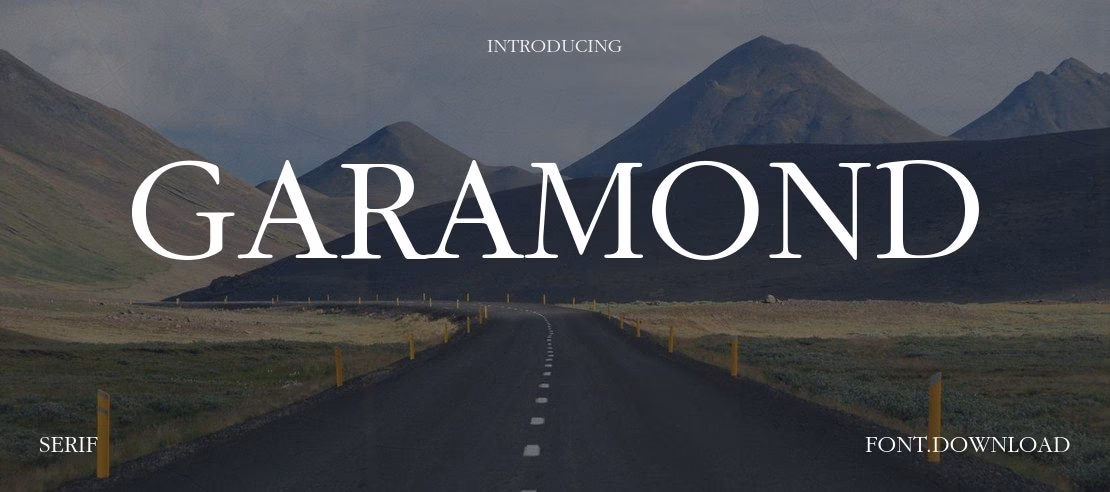
Adobe Systems, grundlagt i 1982 af John Warnock og Chuck Geschke, voksede hurtigt og blev en milliardvirksomhed. Deres succes bygger i høj grad på innovation inden for grafik og teksthåndtering, herunder den revolutionerende PostScript-standard og software som Adobe Illustrator og Photoshop, der blev standardværktøjer for grafiske designere. Introduktionen af Adobe Type Manager (ATM) i 1990 forbedrede visningen af skrifttyper på skærmen markant. Adobe har altid taget typografi meget alvorligt, en dedikation der var tydelig fra begyndelsen.
Under ledelse af Sumner Stone, Adobes typografidirektør fra 1984 til 1991, påbegyndte virksomheden et ambitiøst designprogram. De første skrifttyper i det vigtige Type 1-format blev hentet fra etablerede biblioteker som Linotype og ITC. Endnu vigtigere var initiativet til at genoplive og digitalisere klassiske skrifttyper. Dygtige designere som Robert Slimbach og Carol Twombly, hvis navne er synonyme med fremragende skrifttypedesign, arbejdede på at genskabe historiske perler, herunder Garamond og Caslon. Adobe skabte således sine egne, respekterede versioner af disse klassikere, hvilket cementerede deres position som en central aktør inden for digital typografi. Ud over genoplivninger skabte Adobe også nye, originale skrifttyper som Minion.
Adobe fortsatte med at innovere inden for skrifttypeformater og var medansvarlig for PostScript Type 3 og det spændende Multiple Master-format, der tillod ubegrænset interpolation mellem designvarianter – en sand teknologisk bedrift, selvom udviklingen desværre stoppede i 1999. Fra 1997 arbejdede Adobe sammen med Microsoft om OpenType-formatet. OpenType revolutionerede digital typografi ved at muliggøre smarte erstatninger for tegn (som ligaturer og små kapitæler) og forbedre understøttelsen af mange sprog, hvilket gjorde komplekse typografiske regler tilgængelige digitalt. Adobes OpenType-skrifttyper blev tilgængelige online i 2007.
Apple Inc. har ligeledes en fascinerende historie med skrifttyper, især i relation til deres branding. I over 18 år var Apples primære virksomhedsskrifttype en specialdesignet variant af ITC Garamond kaldet Apple Garamond. Denne skrifttype var tæt forbundet med Apple-brandet og blev brugt overalt – fra logoer og produktnavne på computere til reklamer, trykt materiale og virksomhedens hjemmeside.
Før Apple Garamond eksperimenterede Apple med forskellige visuelle identiteter. Deres tidlige logo med Isaac Newton var håndtegnet og brugte ikke en standard skrifttype, selvom typografien mindede om Caslon. Før introduktionen af den første Macintosh brugte Apple skrifttypen Motter Tektura til deres logo og produktetiketter, kendt fra blandt andet Apple II. Motter Tektura blev valgt for sit legende og teknologiske udtryk, der passede til Apples mission om at gøre teknologi tilgængelig.
Med lanceringen af den første Macintosh i 1984 adopterede Apple så Apple Garamond. Denne variant var baseret på ITC Garamond (designet af Tony Stan i 1977), men var kondenseret til 80% af sin normale bredde og havde en højere x-højde. Bitstream foretog kondenseringen og de nødvendige justeringer. Apple Garamond blev hurtigt synonym med Apples identitet i næsten to årtier. Den blev brugt ikke kun sammen med logoet, men også i manualer, reklamer og på selve produkterne, herunder slogans som det berømte "Think different". Selvom Apple Garamond var så central, har Apple aldrig officielt udgivet den sande skrifttype til offentligheden.
I starten af 2000'erne begyndte Apple gradvist at skifte væk fra den klassiske, serif-baserede Apple Garamond til en mere moderne, sans-serif skrifttype: Adobes egen Myriad. Dette skifte startede omkring 2001 og blev fuldt implementeret i markedsføring og emballage. Myriad-familien, designet af de samme anerkendte typografer fra Adobe, Robert Slimbach og Carol Twombly, som arbejdede på Adobes Garamond-genoplivninger, blev brugt i forskellige vægte, ofte med Myriad Pro Light til overskrifter i de senere år. Apple brugte en modificeret version kaldet Myriad Apple (senere Myriad Set).
Det seneste store skifte i Apples typografiske identitet kom med introduktionen af Apple Watch i 2015, hvor de begyndte at bruge skrifttypen San Francisco. Fra 2016 og frem blev San Francisco gradvist implementeret på tværs af Apples produkter (som "iPhone", "AirPods", "MacBook Pro"), i keynotes, på emballage og på deres hjemmeside. I starten af 2017 blev San Francisco Apple's universelle skrifttype for alle deres produkter, hvilket markerede en fuldstændig overgang fra tidligere valg.
Sammenfattende har både Adobe og Apple haft en dyb indvirkning på typografiens verden. Adobe har ikke kun leveret vigtige værktøjer til designere, men har også bidraget væsentligt til skrifttypebiblioteket med både klassiske genoplivninger (herunder deres version af Garamond) og innovative formater. Apple har på sin side vist, hvordan en skrifttype kan blive en integreret del af et brand, især med det ikoniske Apple Garamond, før de skiftede til Adobes Myriad og senest deres egen San Francisco. Forbindelsen er klar: Adobes designere arbejdede på skrifttyper, som Apple både baserede deres signaturskrifttype på (Garamond) og senere adopterede direkte (Myriad).
Apples Skrifttypehistorie i Overblik
For at give et klart billede af Apples skrifttypeudvikling, her er en oversigt over de mest fremtrædende skrifttyper brugt i deres branding og markedsføring gennem tiden:
Hvem designede de vigtigste skrifttyper for Adobe og Apple?
Mange vigtige skrifttyper for begge virksomheder blev designet af de samme talenter. Robert Slimbach og Carol Twombly designede Adobes Garamond-genoplivninger og Adobes Myriad. Myriad blev senere adopteret af Apple. Apple Garamond var baseret på ITC Garamond (designet af Tony Stan), men modificeret for Apple.